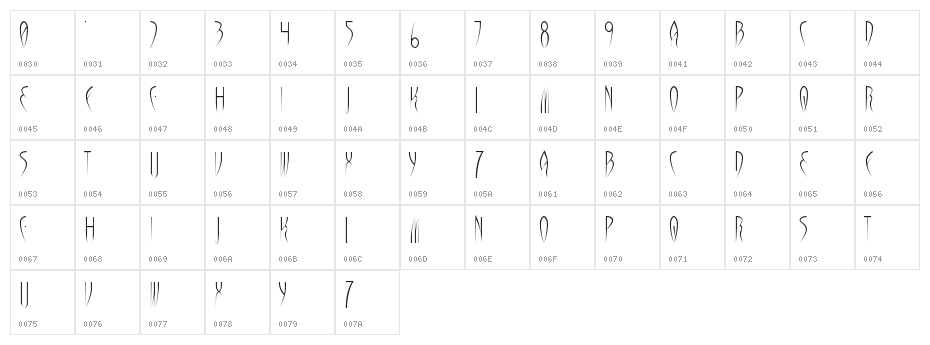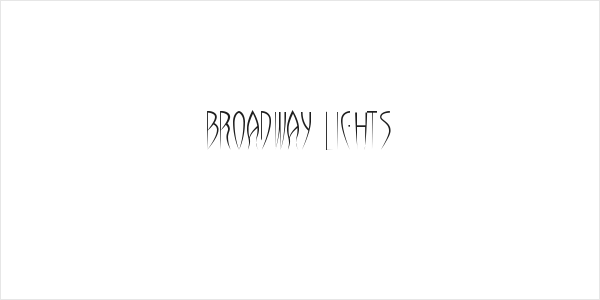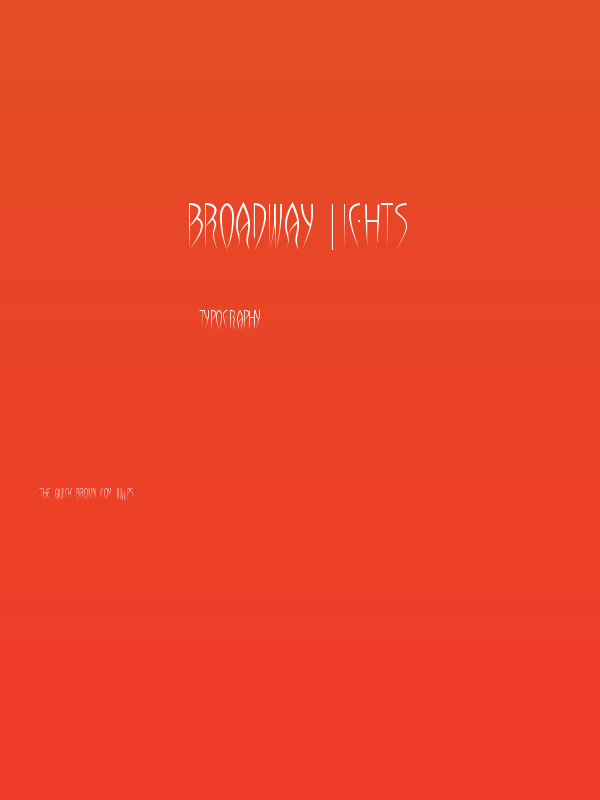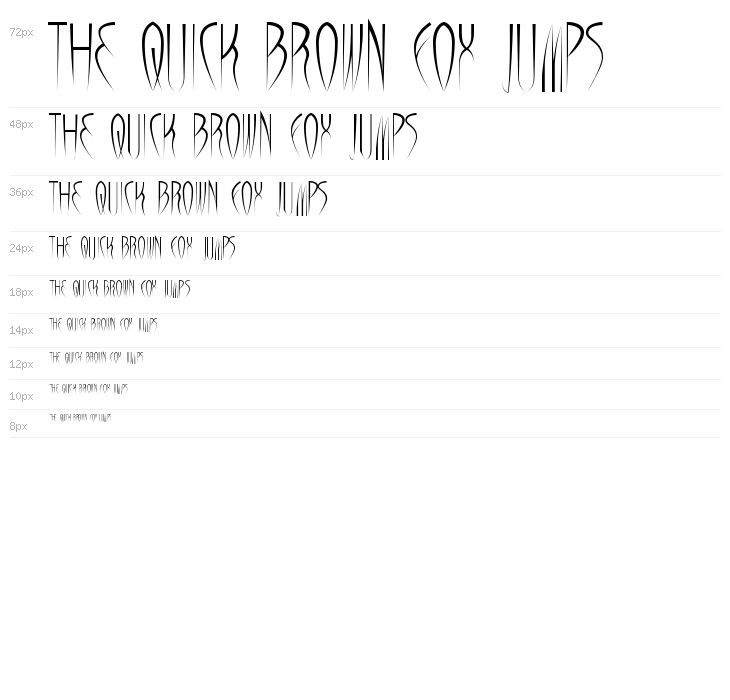
Broadway lights Font
✎ Art Deco
| Estilo general | Vintage |
| Proyectos propuestos | Ideal for theatrical posters, vintage-themed branding, and elegant invitations. |